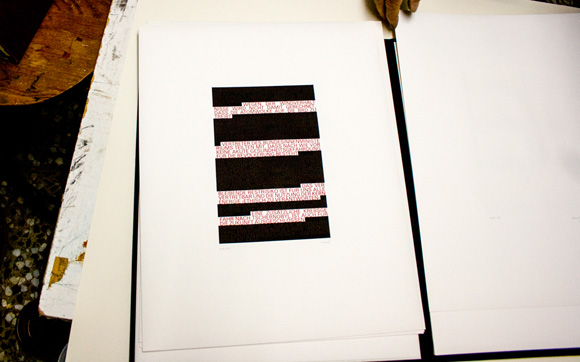
Por lo que sea, últimamente escucho a menudo el nombre de Emilio Sdun. En los últimos años parece que se ha puesto de moda la impresión tipográfica o como le llaman ahora el letterpress.
Haciendo cuentas, parece que este boom ha entrado con fuerza en nuestro país en los últimos 2 ó 3 años. En algunas escuelas como en la de Oviedo o en la de Bellas Artes de Valencia ya se venía trabajando desde antes, pero la mayoría de los pequeños talleres se han abierto apenas hace unos años. En general son iniciativa de gente joven, que se ha hecho con material de imprenta destinado a convertirse en chatarra y a base de reventar tipo de plomo han ido sacando su propia producción. Ya no se imprimen libros o albaranes, sino que se hacen carteles con frases graciosas o tarjetas de visita buscando la veta de la madera y el golpe del plomo sobre el papel.
El uso de la maquinaria de imprenta técnicamente es compleja, y aunque existen manuales de hace un siglo que explican su funcionamiento, la manera habitual de aprender es por medio de un antiguo impresor. Algunos han podido aprender de sus padres, que ya tenían una imprenta y bajo la creencia de que cualquier tiempo pasado fue mejor guardaron todo el material de impresión pensando que algún día serviría para llenar las salas de un museo. Otros se han hecho con un impresor jubilado que de buen grado les ha enseñado cómo se compone un texto, se monta una rama y se ajusta la presión. Y muchos de los que no han tenido ninguna de estas opciones han tirado de Emilio Sdun (Leubnitz, Sajonia, 1944) precursor en España en el uso de la tipografía con fines artísticos y de la autoedición, que armado con su prensa sacapruebas ha impartido talleres por nuestro territorio desde que se afincó en Almería allá por los años 90.
Emilio Sdun en su taller situado en Cuevas del Almanzora, 2008.
En 1996, Dieter Emil Sdun cogió sus bártulos y se mudó buscando el sol. Hasta entonces había trabajado en una imprenta en Berlín que al modernizarse, encontró en Sdun la manera de deshacerse de los chibaletes y las prensas y así dejar paso a la maquinaria de impresión offset. Por entonces, a Sdun ya le gustaba imprimir libros que fueran objetos de arte, donde la letra funcionase como imagen. En 1984 ya había fundado su propia editorial en Berlín Schierlingspresse, cuya particularidad residía en hacer de la tipografía el hilo conductor de sus libros, cuidando tanto la apariencia como el contenido de sus pequeñas obras de arte.
Schierlingspresse realizaba una media de 2 o 3 libros anualmente, y se distinguía de las demás editoriales porque su creador además de ser el artista era el impresor, controlando todo el proceso del libro. A Sdun le preocupaba la forma de sus libros, lo que le llevaba a experimentar con diversos materiales y con los sistemas de encuadernación, realizando multitud de encuadernaciones: tradicionales, carpetas, cajas con páginas sueltas, libros objeto, etc.
Para él era importante hacer libros en los que la disposición de las letras transmitiera ideas y sentimientos; así imprime Transformation (1990), libro dedicado a la catástrofe de Chernóbil donde para expresar en forma de imagen la desinformación que se produce por parte de los medios de comunicación de la época imprime material tipográfico con tinta negra sobreimprimiéndolo a las palabras en rojo. O el libro Mélancolie/Melancholie (1990), donde aparecen dos personajes, una voz fuerte y una baja. Para mostrar las distintas personalidades imprime la primera voz del diálogo, la voz fuerte con futura negrita y para la segunda voz la futura fina, mientras que para los fragmentos del texto utiliza una tipografía neutra, la futura seminegra.
Imagen del libro Transformation, 1987.
Portada y caja del libro Mélancolie/ Melancholie, 1990.
Interior del libro Mélancolie/ Melancholie, 1990.
Rumbo a España, Dieter Emil Sdun deja su Alemania natal, país con tradición en el uso de los tipos móviles con fines artísticos, para adentrarse en el nuestro bajo el nombre de Emilio Sdun donde vive de primera mano el declive del mundo de la imprenta con el cierre la última gran fundición europea, la Fundición Tipográfica Bauer de Barcelona que el 13 de mayo de 2008 dejó de producir tipos móviles. “Compré letras en Barcelona en la fundición Bauer, y el Sr. Hartmann, el gerente me dijo: señor Emilio, es el único en España que compra y realiza sus libros con tipos móviles.”
Aquí, se encontró con un país en el que no existía un mercado del arte destinado al libro de artista, por lo que centraba sus ventas en Europa y Alemania, pero aún así se adentró de lleno en nuestro país trasladando su labor artística a Cuevas del Almanzora y traduciendo el nombre de su editorial como Prensa Cicuta.
Poco a poco y con el paso de los años, Prensa Cicuta se convirtió en una de las pequeñas editoriales cuyo trabajo ha tenido mayor repercusión y reconocimiento a nivel mundial. Los libros de Emilio Sdun se encuentran en grandes instituciones y museos, como en The Tate Gallery de Londres, Victoria and Albert Museum también de Londres, La Biblioteca de Arte de Berlín, El Museo Gutenberg de Maguncia, la Biblioteca Nacional de Baviera en Munich o el Art Center Collage of Design de Pasadena –USA-, entre muchos otros.
Hay que destacar a una persona fundamental en la vida y trabajo de Emilio Sdun, su esposa Doris, que ha ofrecido su tiempo y dedicación para ayudar al editor en la composición, estampación y encuadernación de los libros, acompañándole además durante las diversas ferias y cursos a los que asiste.
Catálogo tipográfico de Prensa Cicuta.
Emilio Sdun trabajando sobre Tyvek, 1988. Extraído del artículo rememorando a Gutenberg, Du Pont Magazine, Número 2, Nyon (Suiza) 1991, Édition Européenne..
Máquina de imprimir Boston- Tiegel Americana, en el taller de Emilio Sdun –Cuevas del Almanzora, Almería-.
La biblioteca del taller de Prensa Cicuta.
Doris Sdun realizando una pancarta impresa con tipografía.
Pero Emilio es un tipo social al que le gusta compartir sus conocimientos con los que le rodean, tanto con los profesionales como con los que se inician en esto de la tipografía. Por ello una labor importante en su trabajo es la de divulgación, por lo que enseña a estudiantes de Diseño y de Bellas Artes los rudimentos básicos de la tipografía, y también por estar siempre rodeado de artistas y escritores con los que Emilio colabora, tanto de nuestro país como de su Alemania natal; para Sdun siempre ha sido importante mantener el contacto y el intercambio de ideas con diversos artistas de su entorno. En su país natal lo revela la revista Schischypusch para la que colaboran multitud de artistas amigos del editor, mientras que en España, sobre todo en los últimos años, este intercambio se ha acentuado de modo que una gran parte de los libros de Prensa Cicuta son colaboraciones tanto de artistas plásticos como de escritores, contando entre ellos con Fernando Arrabal, Úrsula Heinze de Lorenzo y Begoña Crespo, entre otros.
Y me falta destacar sus cartas, donde escribe sobre sus proyectos futuros y del pasado, sobre las personas que le han acompañado en este viaje tipográfico que es su vida y Emilio, mediante su caligrafía esmerada y las palabras llenas de color que redacta desde su Prensa Cicuta nos anima a los que hoy nos iniciamos en la impresión a seguir trabajando y a hacer de la tipografía una forma de vida.
Algunas cartas y regalos enviados por Emilio Sdun a sus amigos.